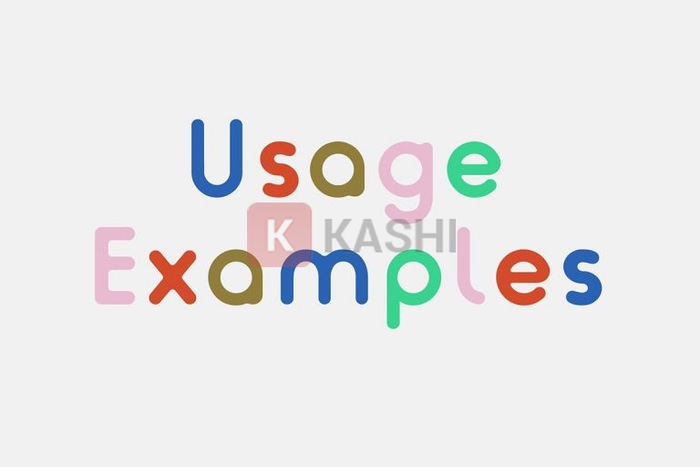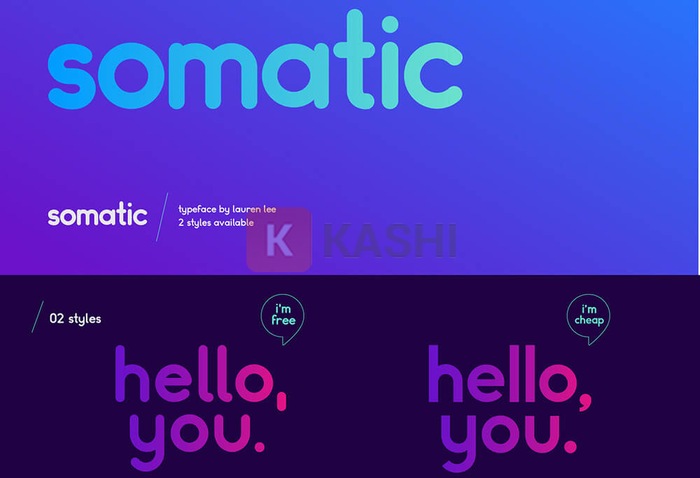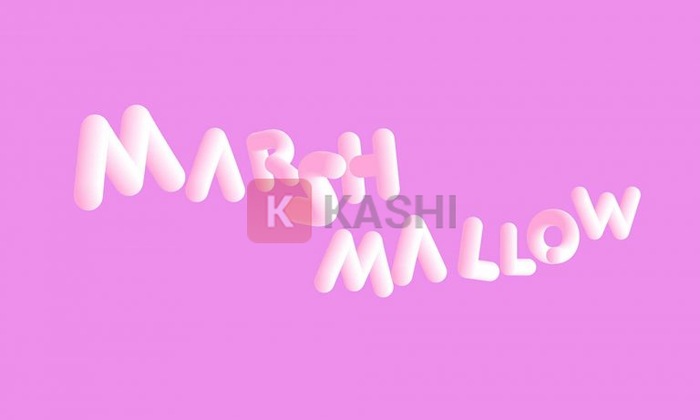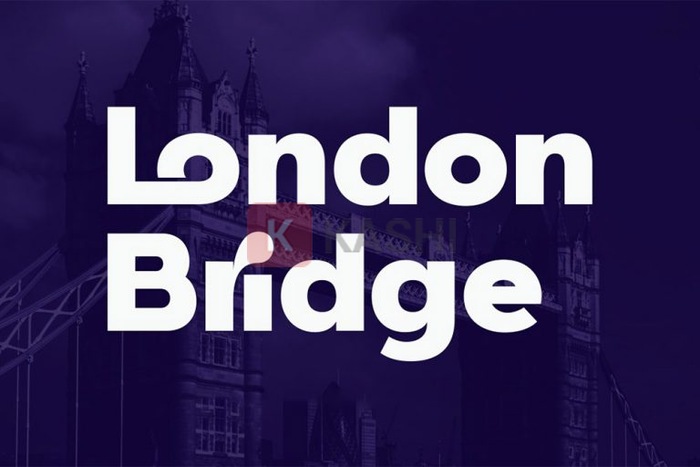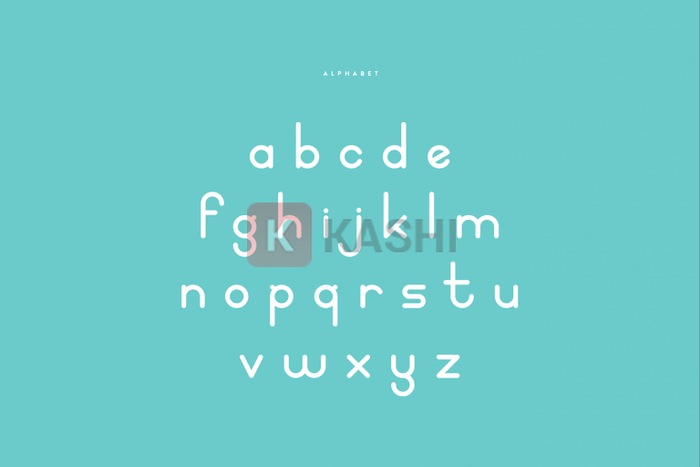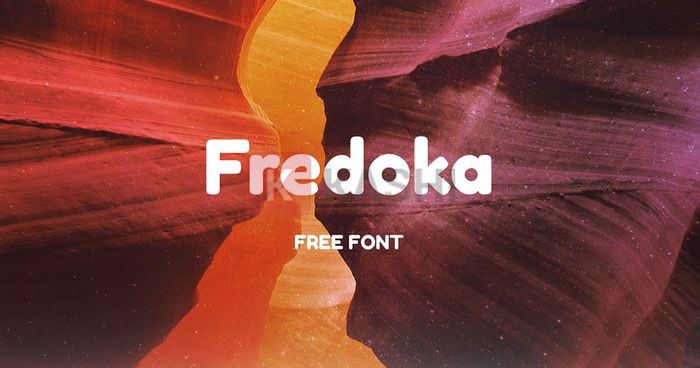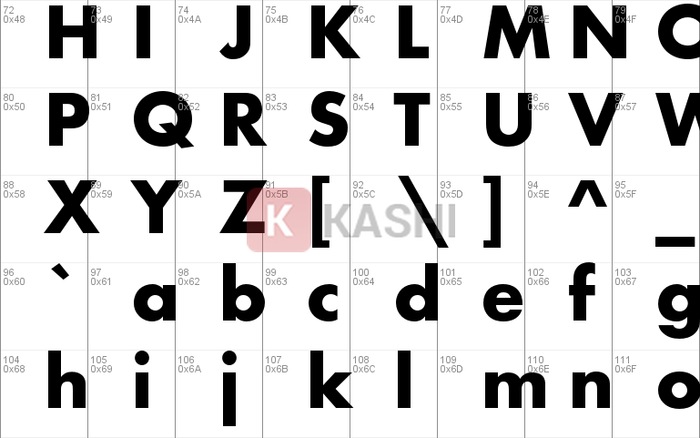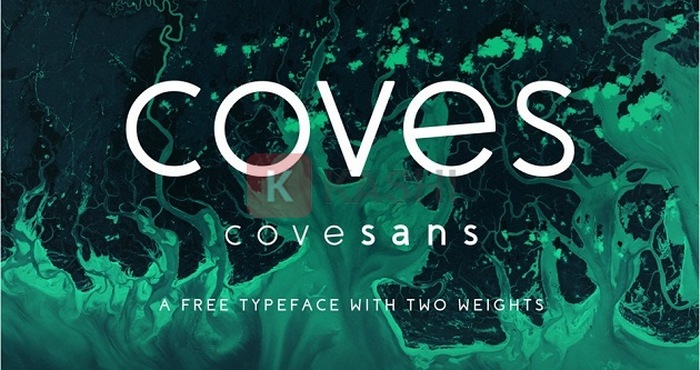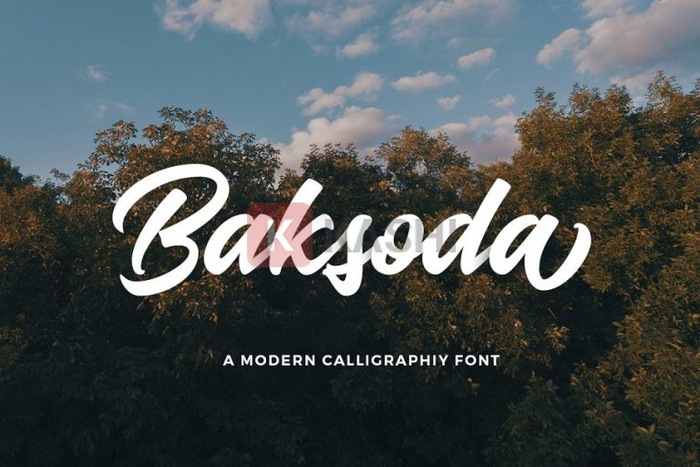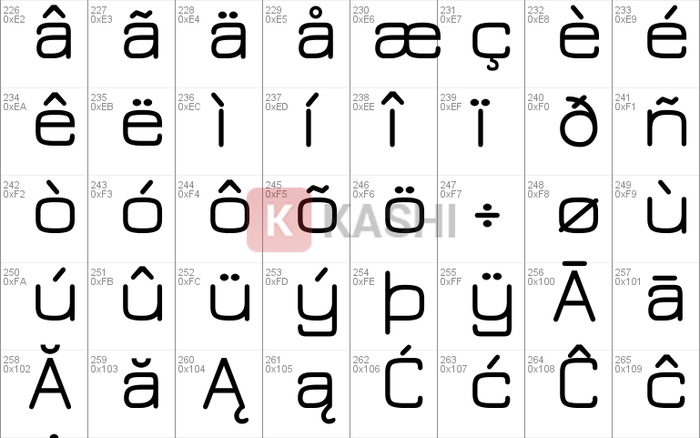
Top 10 Font Chữ Tròn, Béo Đẹp và Miễn Phí Cho Thiết Kế 2025
Bạn muốn thiết kế của mình trở nên hiện đại và thu hút hơn? Font chữ tròn béo là lựa chọn hoàn hảo cho hầu hết các ấn phẩm. Bài viết này sẽ giới thiệu 10 font chữ tròn béo đẹp và ấn tượng nhất hiện nay, cùng với link tải miễn phí.
Font chữ tròn béo là gì? Đúng như tên gọi, đây là kiểu chữ được thiết kế với các nét bo tròn, tạo cảm giác mềm mại, đầy đặn và thân thiện. Kiểu chữ này thường được sử dụng trong thiết kế để tạo điểm nhấn cho tiêu đề, logo, poster, banner quảng cáo, thậm chí cả thiết kế áo phông. Nó mang lại vẻ ngoài hiện đại, tinh tế và dễ đọc, giúp thu hút sự chú ý của người xem.
Tổng Hợp Font Chữ Tròn Béo Việt Hóa Miễn Phí 2025
Dưới đây là danh sách 10 font chữ tròn béo miễn phí, được việt hóa đầy đủ, giúp bạn dễ dàng sử dụng cho các dự án thiết kế của mình.
1. Font Chữ Tròn Somatic
Được thiết kế bởi Lauren Lee, Somatic cho phép bạn tùy chỉnh phần đầu chữ cái là tròn hoặc thẳng, rất phù hợp cho thiết kế logo đơn giản nhưng ấn tượng. Font này cũng rất dễ đọc, thích hợp cho các đoạn văn bản cỡ trung bình.
2. Font Chữ Tròn Yikes
Yikes là font chữ tròn không chân với các nét bo tròn mềm mại, tạo cảm giác vui nhộn và thân thiện. Phù hợp với các thiết kế mang phong cách mới lạ, độc đáo.
3. Font Chữ Tròn Béo Ngộ Nghĩnh Softa
Lấy cảm hứng từ kẹo dẻo, Softa có 10 biến thể màu sắc với độ tương phản ánh sáng và bóng tối độc đáo. Các chữ cái được thiết kế phồng và bo tròn, tạo cảm giác đáng yêu, ngọt ngào, rất phù hợp cho các thiết kế cần sự nổi bật.
4. Font Chữ Tròn Mập Kaige
Được thiết kế bởi Kimmy Lee, Kaige có các nét bo tròn hoàn hảo, lý tưởng cho tiêu đề nhưng không phù hợp với văn bản dài.
5. Font Chữ Bo Tròn Góc London Bridge
London Bridge là một font sans serif hình học hiện đại, có 7 trọng lượng khác nhau, hỗ trợ nhiều ngôn ngữ và ký tự đặc biệt.
6. Font Chữ Tròn Béo Fredoka
Được thiết kế bởi Milena Brandau, Fredoka mang phong cách hiện đại, dễ thương, phù hợp cho thiết kế website, phần mềm và thiết kế số.
7. Font Chữ Béo Baksoda
Baksoda là font chữ viết tay với phong cách rõ ràng và ấn tượng, phù hợp cho thiết kế logo, thiệp mời, bao bì sản phẩm, poster…
8. Font Chữ Tròn Jura
Jura là font chữ tròn thanh lịch với tỉ lệ chữ hẹp, nét bo tròn và chi tiết chân chữ độc đáo. Dễ đọc ở cả kích thước nhỏ và lớn.
9. Font Chữ Tròn Béo Coves
Coves là một font chữ tròn đẹp mắt với các ký tự bo tròn tinh tế. Phần crossline góc cạnh ở chữ “e” tạo điểm nhấn độc đáo.
10. Font Chữ Futura
Futura là font chữ tròn béo phổ biến với vẻ ngoài đậm, tròn trịa và mang đặc trưng hình học. Mang lại cảm giác lạc quan, thân thiện và không bao giờ lỗi thời.